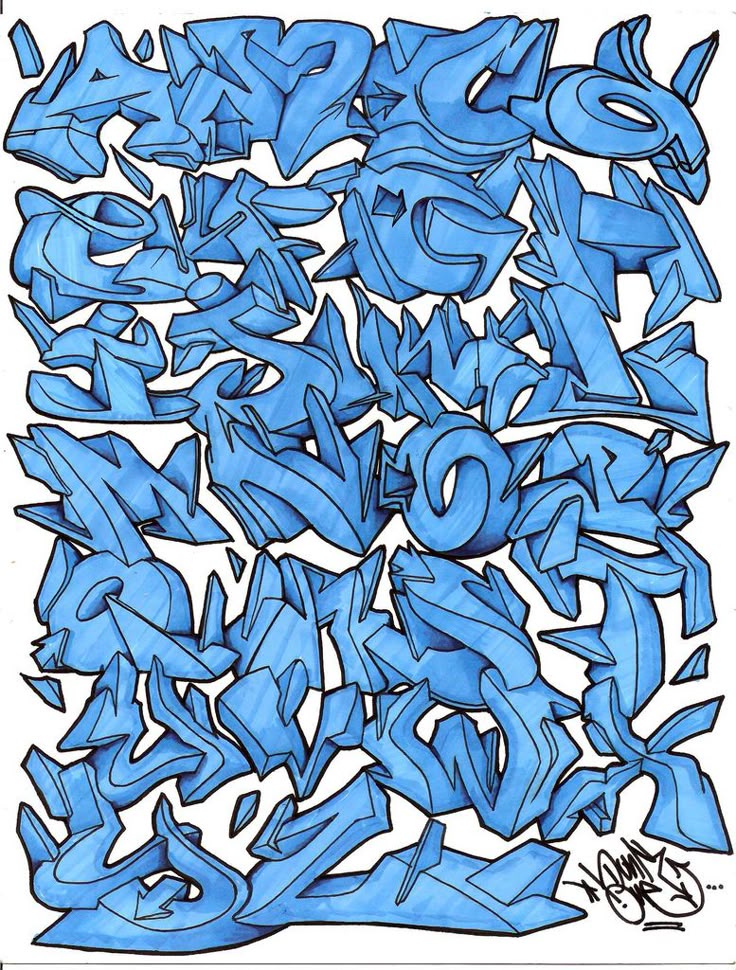
50 лучших граффити-шрифтов для вашего городского дизайна
У нас есть то, что нужно, если вы графический дизайнер и хотите добавить немного уличного стиля в свои городские проекты. Ознакомьтесь с нашей свежей и классной коллекцией граффити-шрифтов.
Что такое граффити-шрифты? По сути, это декоративные шрифты, имитирующие внешний вид уличного искусства. Вдохновленные граффити, они могут выглядеть как аэрозольная краска, каракули или трафареты и часто включают капли краски, эффекты гранжа и брызги для завершения внешнего вида.
Их можно использовать в различных дизайнерских проектах, от логотипов и брендинга до упаковки и одежды.
Граффити уходит своими корнями в вандализм, но со временем оно стало уважаемым видом искусства. Чаще всего это можно увидеть в городских районах и городских районах, поэтому имеет смысл использовать шрифты граффити в дизайне, который требует эстетики уличного искусства.
Когда дело доходит до использования граффити-шрифтов, следует помнить о нескольких вещах. Во-первых, из-за того, что они настолько богато украшены, их может быть трудно читать, особенно в небольших размерах. Поэтому лучше не использовать их для основного текста или других текстовых элементов. Затем соедините граффити-шрифты с простыми шрифтами без засечек для максимальной контрастности и удобочитаемости.
Лучшие шрифты для граффити
Художники граффити имеют уникальный взгляд на мир, и их искусство часто отражает это.
Граффити-шрифты не являются исключением и могут придать вашему дизайну городской оттенок. Вот 50 лучших шрифтов для граффити, которые помогут начать ваш следующий дизайн-проект.
Rollover
Первым идет Rollover, необычный шрифт, который выглядит как капающая краска. И, если вы сделаете шрифт темно-красным, он легко будет выглядеть как кровь, так что он может выполнять двойную функцию в качестве шрифта ужасов. Этот шрифт является хорошим выбором для макетов плакатов, обложек книг, дизайна одежды и многого другого.
Losdol
Вот блочный шрифт граффити в мультяшном стиле, который идеально подходит для того, чтобы придать вашим проектам вид классического граффити, сохраняя при этом достаточно разборчивость для коммерческих проектов. Попробуйте его для одежды, плакатов или логотипов.
Nightfate Graffiti
Nightfate — это большой, жирный и уникальный шрифт, вдохновленный хип-хопом, который добавит городскую атмосферу любому графическому дизайну, в котором вы его используете. Будь то логотип, брошюра, флаер, плакат, обложка книги, или графику в социальных сетях, этот шрифт с заглавными буквами выполнит свою работу.
ZIP-архив со шрифтами содержит прописные буквы, цифры, знаки препинания и веб-шрифт.
Звезда фанки
Это понравится артистам! Funky Star наполнен стилистическими вариантами, поэтому вы можете создать уникальный типографский шедевр с буквами, которые характеризуют веселый и причудливый стиль граффити.
Загрузка включает прописные и строчные буквы, цифры, знаки препинания, альтернативные наборы символов. Он идеально подходит для широкого спектра проектов, таких как афиши мероприятий, обложки альбомов, цитаты, логотипы, брендинг и многое другое.
Загрузка включает прописные буквы, цифры, знаки препинания, многоязычные специальные символы и веб-шрифты.
Notress
Вот декоративный шрифт с аутентичным видом граффити. У него сложные формы букв и интересные формы, которые уникальны для этого стиля письма. Используйте Notress для городской одежды, дизайна логотипов, упаковки, настенного искусства и графики для социальных сетей.
Загрузка шрифта включает прописные буквы, цифры, знаки препинания и веб-шрифт.
Streamzy
Интересный взгляд на жанр! Streamzy сочетает в себе стиль смелого шрифта граффити с игривым видом детского шрифта, что делает его идеальным выбором для дизайна видеоигр, плакатов детских мероприятий, флаеров, обложек детских книг и других беззаботных дизайнов.
Загрузка шрифта включает прописные и строчные буквы, цифры и знаки препинания.
Hayword
Вдохновленный уличным искусством, Hayword представляет собой шрифт в стиле граффити, напоминающий надписи на ярлыках. Попробуйте использовать этот декоративный шрифт для дизайна одежды, настенных цитат, постеров фильмов, графики в социальных сетях, заголовков веб-сайтов и обложек книг.
Этот архив со шрифтами включает прописные и строчные буквы, цифры, знаки препинания и многоязычную поддержку.
Районсайд
Вот еще один шрифт, вдохновленный тегами, который выглядит так, будто был создан маркером. Он был создан, чтобы быть смелым, легко читаемым и идеально подходящим для того, чтобы добавить нотку уличного стиля в ваши проекты. Используйте его для редакционных макетов, графики для социальных сетей, упаковки продуктов, брендинга, логотипов и многого другого.
Загрузка включает символы верхнего регистра, цифры, знаки препинания, альтернативы, лигатуры, многоязычную поддержку и веб-шрифты.
Airneo
Airneo — забавный граффити-шрифт с заглавными буквами и деталями в виде стрелок. Строчные буквы тоже заглавные, но без стрелок. Существует также полный набор альтернативных глифов со стрелками, указывающими в противоположном направлении, поэтому вы можете начинать и заканчивать свою типографику со стрелками, указывающими так, как вы хотите.
Загрузка шрифта включает все заглавные буквы, цифры, знаки препинания, альтернативные варианты и многоязычную поддержку.
Бесстрашная королева
Бесстрашная королева — это брашированный шрифт с атмосферой граффити и ретро-эстетикой. Он идеально подходит для дизайна, связанного с музыкой, например флаеров концертов, плакатов, постов в социальных сетях и обложек альбомов. Но не ограничивайтесь только музыкальным дизайном — он также подходит для рекламы, цитат и брендинга.
Загрузка включает все прописные буквы, цифры, знаки препинания, лигатуры, многоязычную поддержку и веб-шрифты.
Darksite
Этот городской граффити-шрифт идеально подходит для дизайна упаковки, футболок, постеров, графики для социальных сетей, логотипов и многого другого.
Darksite имеет классический вид граффити с тегами и включает в себя бонусный шрифт swash, чтобы придать вашим проектам еще большую достоверность.
Загрузка включает все прописные буквы, цифры, знаки препинания, многоязычную поддержку, веб-шрифт и бонусные росчерки.
Offstoke
Это однострочный шрифт среднего размера в стиле граффити, который добавит городскую нотку вашим коммерческим и личным проектам. Используйте его для графики в социальных сетях, цитат, заголовков веб-сайтов и обложек видео на YouTube.
Загрузка включает прописные и строчные буквы, цифры и знаки препинания.
Luser Graffiti Bold
Вдохновленный современным уличным искусством и музыкой хип-хоп, Luser представляет собой смелый шрифт для граффити, отличающийся короткими игривыми буквами. У этого есть атмосфера граффити, но его довольно легко читать, поэтому используйте его для заголовков, редакционных макетов, листовок, плакатов, цитат и дизайна одежды.
Загрузка включает прописные буквы, цифры, знаки препинания и веб-шрифты.
Dripster
Вот шрифт для тегов граффити, который станет отличным дополнением к вашему дизайнерскому портфолио. Создатель Dripster воспользовался ссылками из различных граффити для создания этого классного шрифта, который обязательно добавит изюминку вашему дизайну, вдохновленному граффити, будь то логотип, бренд одежды, дизайн 80-х, цитата или флаер.
Загрузка шрифта включает заглавные буквы, цифры и знаки препинания.
Стены Техаса
Стены Техаса — это начертание шрифта граффити с фристайловыми характеристиками классического уличного искусства, такими как уникальные перекрывающиеся формы и капающая краска. Это отличный выбор для брендов городской одежды, обложек альбомов и вывесок.
Загрузка шрифта включает прописные буквы, цифры, знаки препинания, лигатуры, альтернативы, многоязычные акценты и веб-шрифт.
Lodstay
Lodstay — еще одна форма граффити-шрифта в стиле уличных тегов с забавной атмосферой, что делает его хорошим выбором для всего: от комиксов до детских книг, листовок с музыкой в стиле хип-хоп и обложек альбомов.
Попробуйте этот с дизайном одежды, упаковкой и логотипами.
Загрузка шрифта включает прописные и строчные буквы, цифры, знаки препинания и многоязычную поддержку.
Street Hipster
Если вы ищете нарисованный от руки шрифт в стиле граффити, который легко читается, но при этом имеет бунтарский резкий вид, вы его нашли! Street Hipster — отличный выбор для заголовков веб-сайтов, афиш мероприятий, обложек альбомов, графики для социальных сетей и вывесок.
Застежка-молния со шрифтом поставляется с прописными и строчными буквами, цифрами, пунктуацией и многоязычной поддержкой.
Bomber Squad
Bomber Squad — это трехмерный шрифт в забавном мультяшном стиле граффити. Он поставляется с версиями сплошного и теневого контура, которые вы можете комбинировать для создания трехмерного вида. Этот шрифт — отличный выбор для постеров, флаеров, комиксов, обложек книг и любых коммерческих проектов.
Загрузка содержит все заглавные буквы, цифры, знаки препинания и многоязычную поддержку.
Arcinoll
Этот беззаботный и забавный шрифт представляет собой рукописный маркерный шрифт, вдохновленный уличным искусством и граффити. Это отличный выбор для цитат, рекламных листовок, одежды, плакатов, графики для социальных сетей и любых других проектов, требующих немного шика.
ZIP-файл включает все заглавные буквы, цифры, знаки препинания, лигатуры, многоязычную поддержку и веб-шрифт.
НЕОГРАНИЧЕННАЯ ЗАГРУЗКА: более 50 миллионов надстроек и элементов дизайна
The Ponkys
Если ваш дизайн требует яркого шрифта с жирным шрифтом, отличительными символами и стилями граффити, попробуйте The Ponkys . Этот уникальный шрифт с заглавными буквами имеет аутентичный уличный стиль, который может вывести ваш дизайн на новый уровень.
Загрузка шрифта включает все заглавные буквы, цифры, знаки препинания, росчерки и многоязычную поддержку.
Hokia
Hokia — еще один шрифт для тегов граффити, идеально подходящий для упаковки продуктов, брендинга, графики в социальных сетях, логотипов, цитат и других проектов, требующих острой и крутой городской эстетики.
ZIP-файл включает прописные и строчные буквы, цифры, знаки препинания и многоязычную поддержку.
The Bold Street
Этот акцидентный шрифт в стиле граффити может быть вдохновлен уличным искусством, но его милые мультяшные персонажи-пузыри хорошо подходят для детских книг, комиксов и упаковки детских товаров. Конечно, это также хорошо сработает и для городских проектов.
Шрифт включает прописные и строчные буквы, цифры, знаки препинания, многоязычную поддержку и веб-шрифт.
Southsider
Используйте такой шрифт, как Southsider, чтобы добавить дополнительный характер и сделать ваш дизайн по-настоящему ярким! Вдохновленный музыкой хип-хоп и стилем граффити, этот дисплейный шрифт имеет ярко выраженный уличный стиль, но сохраняет разборчивые буквы, что делает его отличным выбором для заголовков, редакционных макетов, листовок, плакатов и многого другого.
Загрузка включает прописные и строчные буквы, цифры и знаки препинания.
Throws
Если вы ищете аутентичные граффити-шрифты в стиле Throws, Throws — это то, что вам нужно! Stack Throws Fill и Throws Line для достижения внешнего вида.
Кернинг и интервалы плотные, как настоящие на улицах. Это не становится намного более реалистичным, чем это.
Загрузка шрифта включает два шрифта — Throws Fill и Throws Line, с прописными и строчными буквами, цифрами и пунктуацией.
Hidebeast
Hidebeast — это жирный и крупный нарисованный от руки шрифт, вдохновленный граффити, который представлен в двух стилях — контурном и блочном. Его громкое, веселое, мультяшное качество делает его хорошим выбором для упаковки энергетических напитков, комиксов, дизайна видеоигр, постов в социальных сетях, плакатов и всего остального, что требует веселого и прикольного шрифта с городским оттенком.
Загрузка включает оба шрифта с прописными и строчными буквами, числами, пунктуацией, многоязычной поддержкой и веб-шрифтами.
East Coast Wild Style
East Coast Wild Style — это рукописный шрифт для тегов, воплощающий уличный стиль. Он включает в себя бонусный набор штрихов, которые вы можете использовать для еще большей достоверности.
Этот шрифт трудно читать, и он должен быть таким, поэтому используйте его осторожно — для флаеров, обложек альбомов, дизайнов футболок и многого другого.
Почтовый индекс включает прописные и строчные буквы, цифры, знаки препинания и росчерки.
Bembies
Это однолинейный маркерный шрифт от легкого до среднего, вдохновленный свободным и плавным стилем граффити. Bembies хорошо подойдут для дизайна в стиле хип-хоп, приглашений на вечеринки, листовок с мероприятиями, дизайна футболок, комиксов, графики для социальных сетей и настенного искусства.
Загрузка шрифта включает в себя все заглавные буквы, цифры, знаки препинания и многоязычную поддержку.
RaseOne
Семейство шрифтов RaseOne представлено в пяти стилях — Fill, Fade, Color, Fat 3D и Outline, что дает вам множество вариантов дизайна. Сам шрифт довольно уникален, он немного похож на нечто среднее между шрифтом граффити и шрифтом в стиле татуировки. Вы также получаете множество специальных символов, таких как стрелки, завитки и начальные и конечные полосы для ваших букв.
Это воплощение мечты любителя типографики. Загрузка включает пять шрифтов с прописными и строчными буквами, цифрами и пунктуацией.
Street Explorer
Street Explorer вдохновлен граффити на городских улицах. Пухлые пузырчатые буквы характерны для стиля граффити, известного своими простыми формами, которые можно быстро «выбросить». Симпатичные круглые буквы будут хорошим выбором для любого дизайна, который требует граффити, но они также хорошо подойдут для детских проектов.
ZIP-файл содержит прописные и строчные буквы, цифры, знаки препинания, лигатуры, альтернативы и веб-шрифт.
Night Vandal
Используйте этот великолепный граффити-шрифт, чтобы вывести свой городской дизайн на новый уровень. Как следует из названия, Night Vandal был вдохновлен уличным искусством и действительно имеет вид классического граффити. Попробуйте этот для создания уникальных логотипов и монограмм или городского дизайна футболок.
Загрузка включает все заглавные буквы, цифры и знаки препинания.
Basketor
Если вы все еще ищете что-то необычное, как насчет этого монолинейного маркерного шрифта с изюминкой… эти буквы, вдохновленные уличным искусством, выглядят стильно! Они сочатся от дерзости! Basketor — отличный выбор для спортивных логотипов, винтажных дизайнов, брендинга, флаеров и плакатов.
Загрузка шрифта включает прописные и строчные буквы, цифры, знаки препинания и многоязычную поддержку.
Snikers
Вот шрифт граффити в стиле каллиграфического маркера, который вы можете использовать, чтобы легко включить стиль уличного искусства в свой дизайн. Созданный настоящим художником-граффити, Snikers — отличный выбор для рекламы, редакционных макетов, графики для социальных сетей, дизайна одежды и логотипов.
ZIP-архив со шрифтами включает в себя все заглавные буквы, цифры, знаки препинания, росчерки, многоязычную поддержку и веб-шрифты.
Rhieknuza
Rhieknuz — это крутой и причудливый шрифт, вдохновленный граффити, в котором есть все необходимое для придания урбанистического вида вашим проектам.
Более того, это вполне разборчиво, но при этом выглядит как стрит-арт. Это хороший выбор для дизайна одежды, цитат, макетов журналов, плакатов и многого другого.
Загрузка включает прописные и строчные буквы, цифры, знаки препинания и веб-шрифт.
Morfem
Morfem — это шрифт для тегов граффити, который идеально подходит для всего: от брендинга продуктов до заголовков веб-сайтов, видеоигр, графики в социальных сетях и многого другого. Используйте его всякий раз, когда ваш графический дизайн требует свежего, резкого, мятежного и городского шрифта.
ZIP-файл включает прописные и строчные буквы, цифры, знаки препинания, росчерки, многоязычную поддержку и веб-шрифты.
Wushand
Вот еще один граффити-шрифт в стиле «throw up», характеризующийся толстыми, округлыми, пухлыми буквами и очень плотным кернингом. Используйте его для дизайна футболок, настенного искусства, графики для социальных сетей и многого другого.
Загрузка шрифта включает все заглавные буквы, цифры, знаки препинания и веб-шрифты.
Boomsplash
Граффити-шрифт Boomsplash — идеальный шрифт для добавления ощущения уличного искусства в ваши проекты — буквы наносятся из баллончика с краской, что придает им ощущение подлинного граффити. Это также очень разборчивый шрифт, так что это хороший выбор для многих коммерческих проектов.
ZIP-файл включает прописные и строчные буквы, цифры, знаки препинания, росчерки и многоязычную поддержку.
Maxtield
Maxtield — маркерный шрифт среднего размера с влиянием уличного искусства. Это фантастический вариант для обложек альбомов, дизайнов футболок, флаеров, плакатов, настенных рисунков, цитат, поздравительных открыток, проектов брендинга и многого другого.
Этот загружаемый шрифт включает прописные буквы, строчные буквы, цифры, знаки препинания, росчерки, брызги и стрелки, а также веб-шрифт.
The Overcook
Этот фристайловый городской маркерный шрифт — отличный выбор для обложек альбомов, графики веб-сайтов, цитат, дизайнов футболок и постеров.
Соедините его с простым шрифтом без засечек и используйте его везде, где хотите привнести городской стиль.
Заархивированный шрифт содержит прописные и строчные буквы, цифры, знаки препинания, лигатуры, альтернативы, многоязычную поддержку и веб-шрифт.
Warxer
Если вы хотите придать своим рисункам ощущение подлинности кисти ручной работы, шрифт Warxer Graffiti — отличный выбор. Он наполнен уникальным стилем с множеством штрихов, но при этом легко читается. Используйте его для создания логотипов, заголовков, дизайна упаковки, типографских цитат, обложек книг и дизайна одежды.
Загрузка включает все заглавные буквы, цифры, знаки препинания, множество лигатур, альтернативные символы и многоязычную поддержку.
Most Wanted
Вот еще один великолепный декоративный дисплейный шрифт с резким урбанистическим граффити. Используйте Most Wanted для создания привлекательных флаеров событий и графики для социальных сетей, дизайнов упаковок, цитат и многого другого.
Загрузка шрифта включает прописные и строчные буквы, цифры, знаки препинания, альтернативные символы, росчерки и многоязычную поддержку.
Nutty Noisses
Nutty Noisses может иметь глупое название, но это очень крутой маркерный шрифт в уличном стиле. Этот нарисованный от руки шрифт, вдохновленный граффити старой школы, отлично подходит для афиш мероприятий и музыкальных афиш, обложек альбомов, дизайна одежды и многого другого.
Загружаемый файл включает прописные и строчные буквы, цифры, знаки препинания, альтернативные символы, лигатуры, многоязычную поддержку и веб-шрифт.
Бесплатные шрифты для граффити
От классических шрифтов для тегов до современных стилей для всплывающих окон — для любых нужд найдется шрифт премиум-класса для граффити. И нет недостатка в отличных бесплатных шрифтах для граффити. Ниже приведены некоторые из наших любимых. Просто всегда проверяйте лицензию перед использованием любого бесплатного шрифта в коммерческом проекте, потому что некоторые шрифты могут быть бесплатными только для личного использования.
Painterz
Painterz — это созданный вручную шрифт в стиле граффити с каплями мокрой краски. Это верный способ добавить немного стиля уличного искусства в ваш графический дизайн.
Jamtreet Graffiti
Jamtreet Graffiti выглядит так, будто нарисовано маркером. Этот шрифт для тегов граффити — отличный выбор для дизайна, связанного с музыкой.
Bombing
Этот шрифт кисти в стиле граффити — отличный выбор для всех видов проектов, таких как комиксы, графика для социальных сетей, эскизы видео и многое другое.
Docallisme On Street
Оцените этот крутой 3D-граффити-шрифт! Это может быть идеально для видеоигр, обложек детских книг, настенного искусства и дизайна упаковки.
Attack Graffiti
Вот еще один шрифт, вдохновленный фристайл-граффити, который включает в себя свежую капающую краску.
Most Wasted
Most Wasted — это вдохновленный уличными тегами шрифт для граффити, который поможет вашим проектам выделиться из толпы.
Используйте это в большом размере, чтобы убедиться, что он остается разборчивым.
Smilen
Этот многослойный маркерный шрифт в стиле граффити выделяется жирным шрифтом, легко читается и поддерживает несколько языков. Это не всегда легко найти с бесплатным шрифтом.
South Crew
South Crew — это шрифт кисти в стиле граффити, но этот более жирный, чем большинство других, и содержит настоящие прописные и строчные буквы.
Начните использовать эти граффити-шрифты уже сегодня